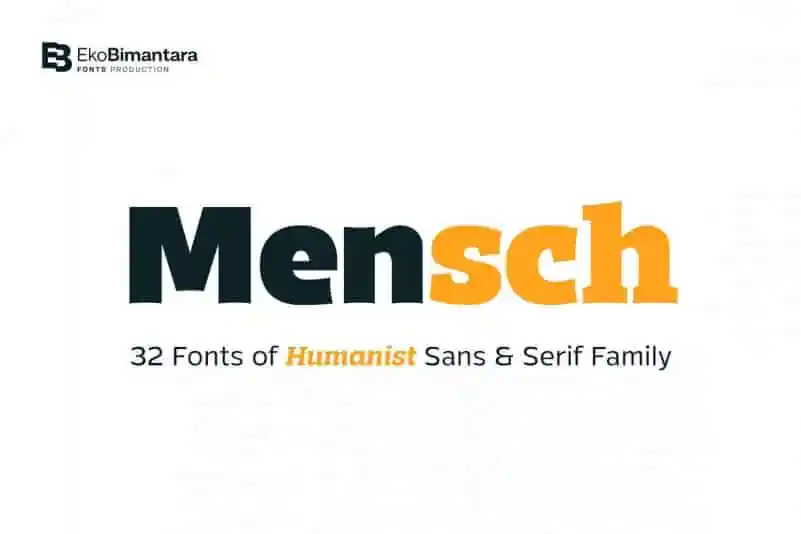
Mensch Sans Serif Font – Download Grátis
A Mensch Sans Serif Font é uma escolha ideal para quem busca uma fonte com um aspecto moderno e bold sem perder a contraste característico do tipo serifado. Com seu corpo extremamente bold, mas ainda assim mantendo uma alta contração, essa fonte destaca-se por seus caracteres expressivos e divertidos, que se manifestam através de suas formas tipográficas. Um destaque é sua altura grande para x, altura baixa das caps e espaçamento entre as câmaras e aberturas, características marcantes definidas pelo uso de pontas e falhas paralelas à horizontal. Perfumada para uso em grandes telas também como fonte para leitura em pequenas dimensões, a Mensch apresenta 32 tipos distintos, incluindo serifados, com pesos que vão desde fino até preto, cada um acompanhado de sua itálica correspondente. Além disso, oferece mais de quatrocentas e cinquenta formas gíliacas compatíveis com uma variedade linguística latina vasta. Esta fonte da 99designs é uma opção perfeita para projetos que exigem um visual moderno e agressivo, mas que ainda assim querem manter a legibilidade em grande escala ou leitura confortável em pequenos tamanhos.